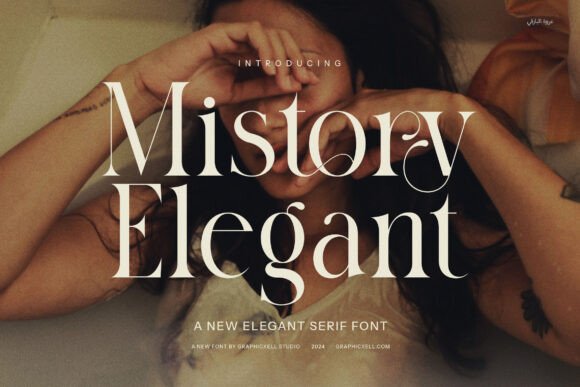
Mistory Elegant Font
Si vous recherchez des ressources de haute qualité comme Mistory Elegant Font, ce pack premium est un choix fantastique pour vos projets créatifs.
Que vous créiez des produits POD (impression à la demande), des invitations de mariage ou des visuels pour les réseaux sociaux, Mistory Elegant Font est un choix idéal.